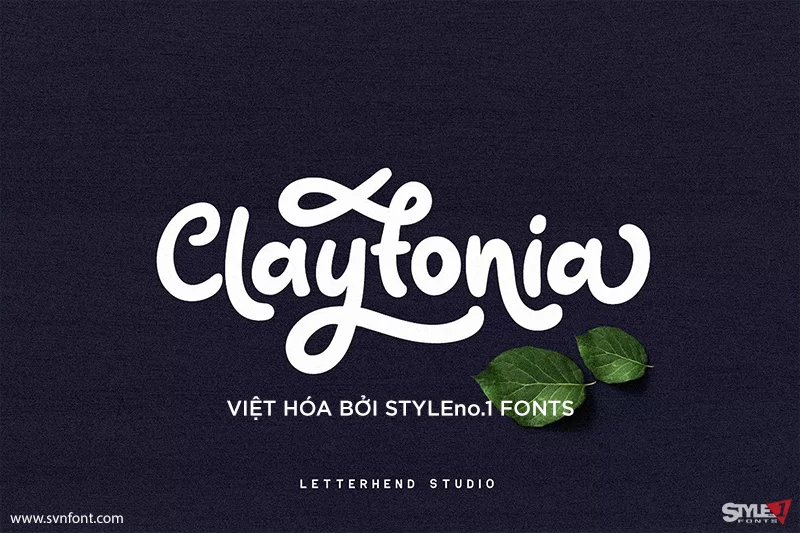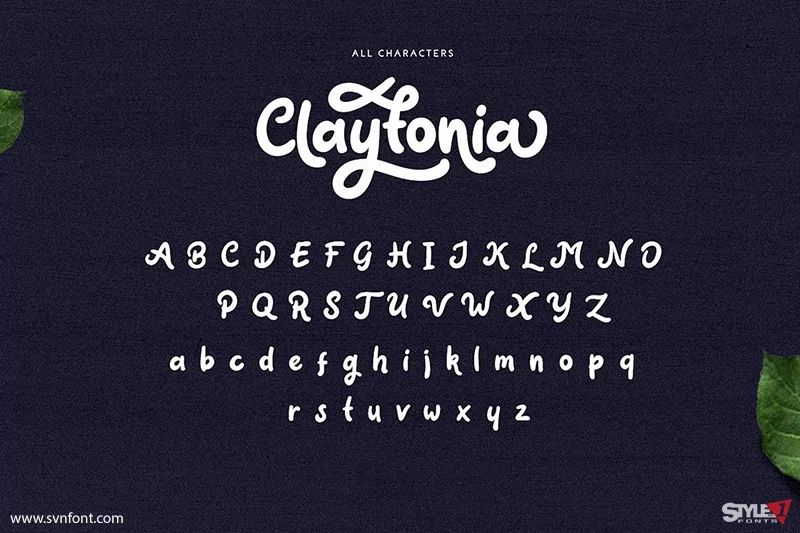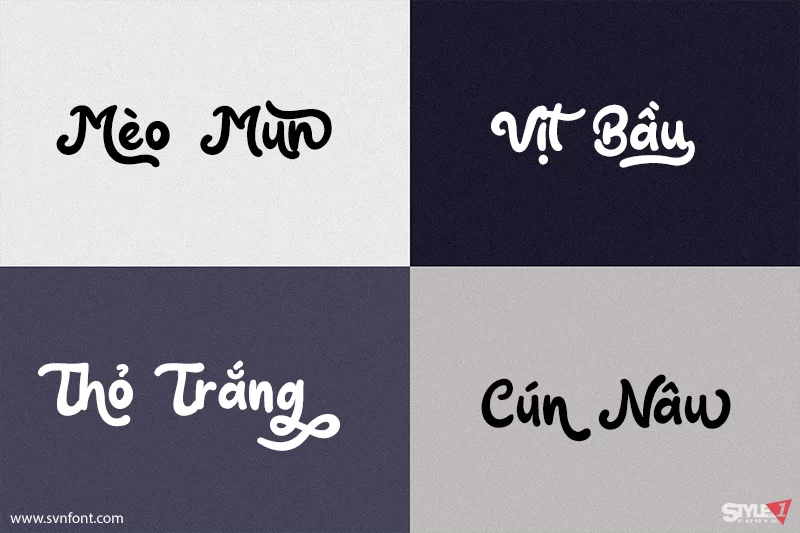
Claytonia là một kiểu chữ chữ đậm, đơn giản nhưng rất đẹp. Làm bằng tay viết với nhiều tính năng opentype mà bạn sẽ thích.
Phông chữ này hoàn hảo như biểu tượng, thiết kế trang phục, thiệp mời đám cưới và nhiều thứ khác nữa. Bạn có thể chơi với các chữ ghép, thay thế phong cách, swash, vv để tạo chữ tùy chỉnh của riêng bạn. Phông chữ này cũng sẽ hỗ trợ đa ngôn ngữ.
Nhà thiết kế: Hendry Juanda
Nhà phát hành: Letterhend
Việt hóa: STYLEno.1 Fonts